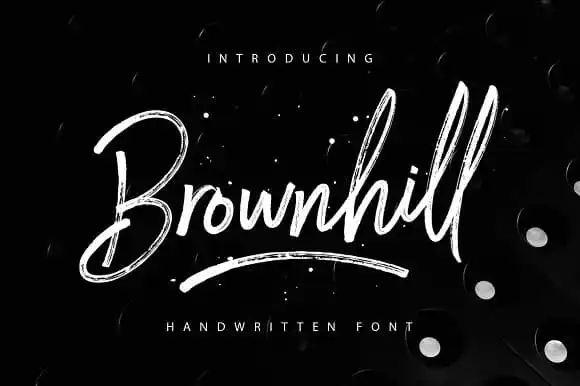
A fonte ‘Brownhill Script Font’ é uma delícia para quem procura estilo próprio e originalidade, perfeitamente adaptada a diversas aplicações. Ela foi criada pelo designer 178-MC como um tipo de script elaborado pela Brownhill, apresentando o máximo de elegância na forma manual de escrever. Perfeita tanto para logos quanto para nomes de etiquetas manuscritas, ela se destaca no design de produtos customizados, etiquetas em papel, cartões de boas-vindas e até mesmo as redes sociais. Suas características permitiram economizar tempo significativamente ao criar qualquer produto que esteja ligado à arte manual. Com uma coleção completa de letras maiúsculas e minúsculas, além de um grande número de pontuações e números, essa fonte garante suporte para múltiplos idiomas. É ideal para quem busca uma maneira rápida e prática de adicionar seu próprio toque pessoal às criações digitais, mantendo assim a essência autêntica das artes manuscritas tradicionais.